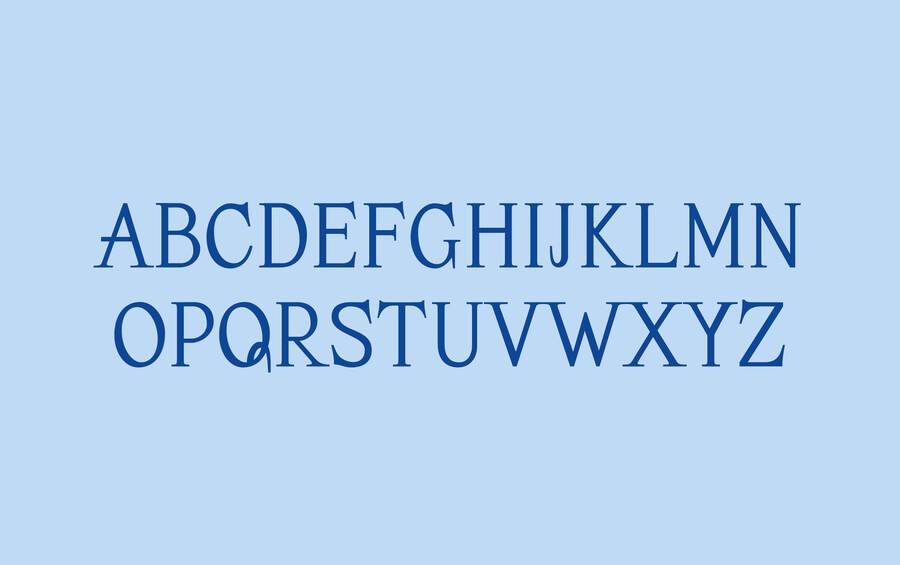
Absurdite font
Absurdite — акцидентная антиква, созданная для пьесы театра абсурда «Лысая певица» Эжена Ионеско. Шрифт передает ощущение абсурда и диссонанса благодаря игре с «запрещенными» приемами.
Первоначально шрифт задумывался для использования в крупном размере: для плакатов, заголовков в печатных изданиях. Но так как «Лысая певица» была написана Ионеско во время изучения английского языка по методу Ассимиль, то необходимо было сделать антикву также текстовой, чтобы сохранить отсылку к учебникам для изучения языков.
Шрифт поддерживает русский и французский языки
Absurdite включает в себя три дополнительных сета